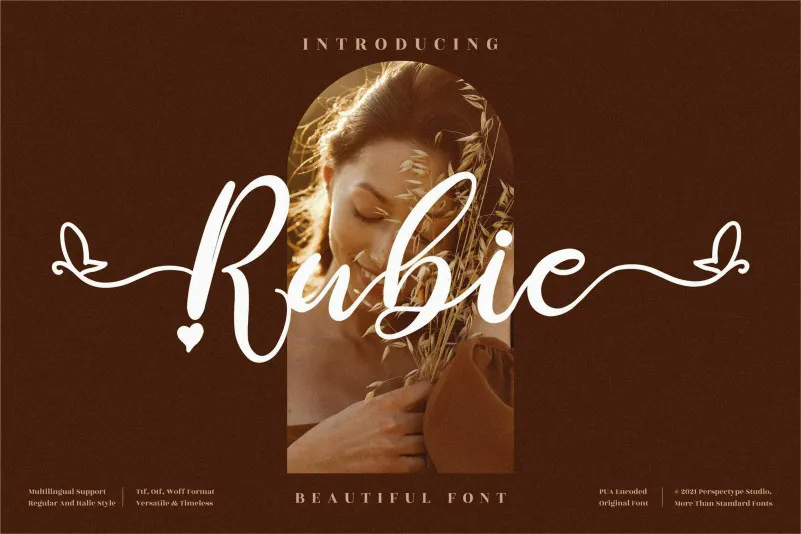
Esta fonte Script é delicada e meticulosamente feita. Com seus traços detalhados e sua codificação PUA, Rubie oferece uma vasta gama de caracteres e swashes que podem ser acessados facilmente. Este esplêndido recurso para o seu acervo de fones pode enriquecer qualquer criação. Não importa o tema, esta font é um tesouro valioso para os designers. Com Rubie à sua disposição, você terá a habilidade de dar vida à suas ideias de uma maneira única e impactante, tornando cada projeto mais fascinante.